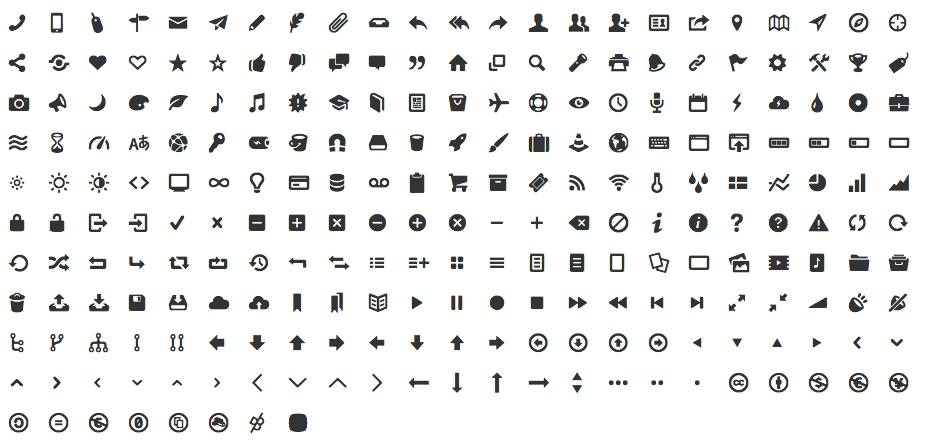
Начало работы с Font Awesome
Иконочные шрифты, альтернативы FontAwesome
Что такое «Иконочный шрифт» — это обычный шрифт, но вместо букв и цифр в нем отображаются различные пиктограммы и символы. В последние годы такие шрифты активно используют в веб-дизайне, в качестве иконок для сайта. С их помощью можно улучшить юзабилити сайта, упростить восприятие информации. Еще из плюсов использования иконочных шрифтов по сравнению с иконками-картинками:
- Возможность масштабирования без потери качества
- Беспроблемная поддержка в большинстве браузеров
- Возможность стилизации, работа как с обычным текстом
- Небольшой вес
- Всего за один запрос на сервер загружаются все необходимые иконки
Самый популярный иконочный шрифт FontAwesome https://fontawesome.com/, но поскольку информации о нем и так полно, мы лучше рассмотрим альтернативные шрифты.
Этот шрифт в качестве иконок содержит логотипы различных интернет и ИТ брендов.
Шрифт поставляется с CSS, поэтому у вас есть возможность его кастомизации. Иконки шрифта можно использовать без фона или с фоном сделав из квадратными, с закругленными концами и просто круглыми.
Резюме
В сообществе все еще ведутся споры о том, лучше ли иконочные шрифты, чем SVG, или наоборот.![]()